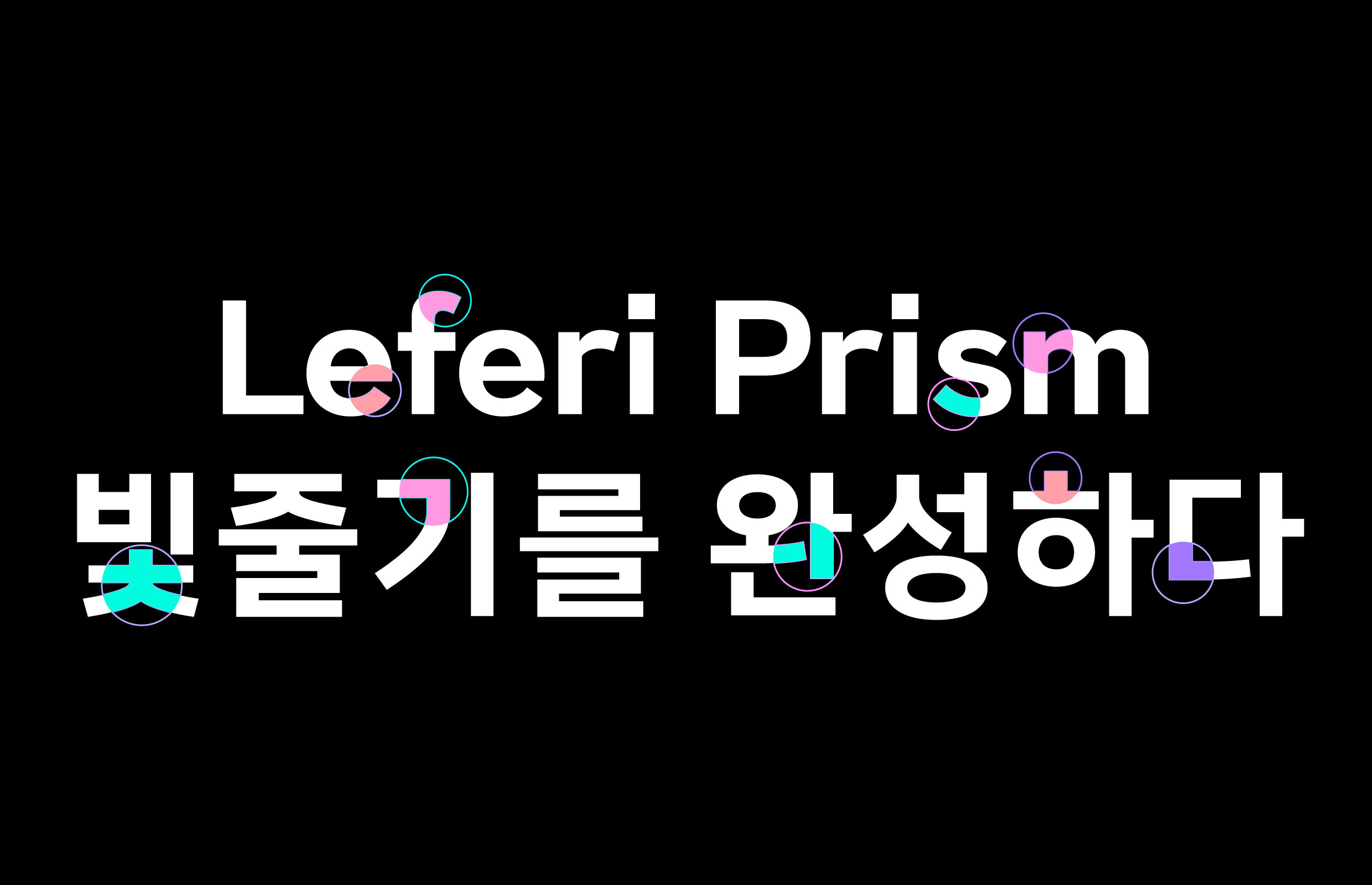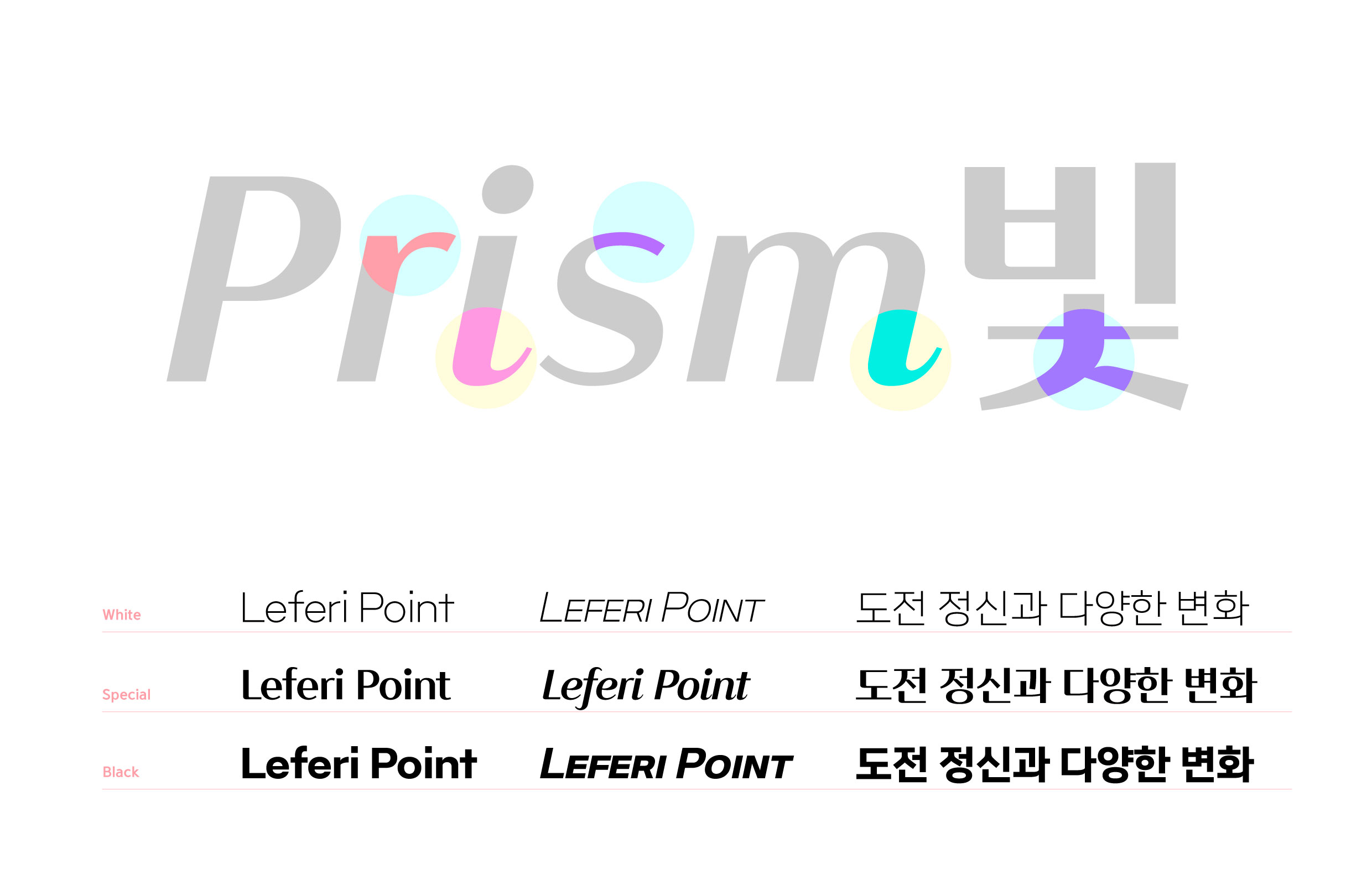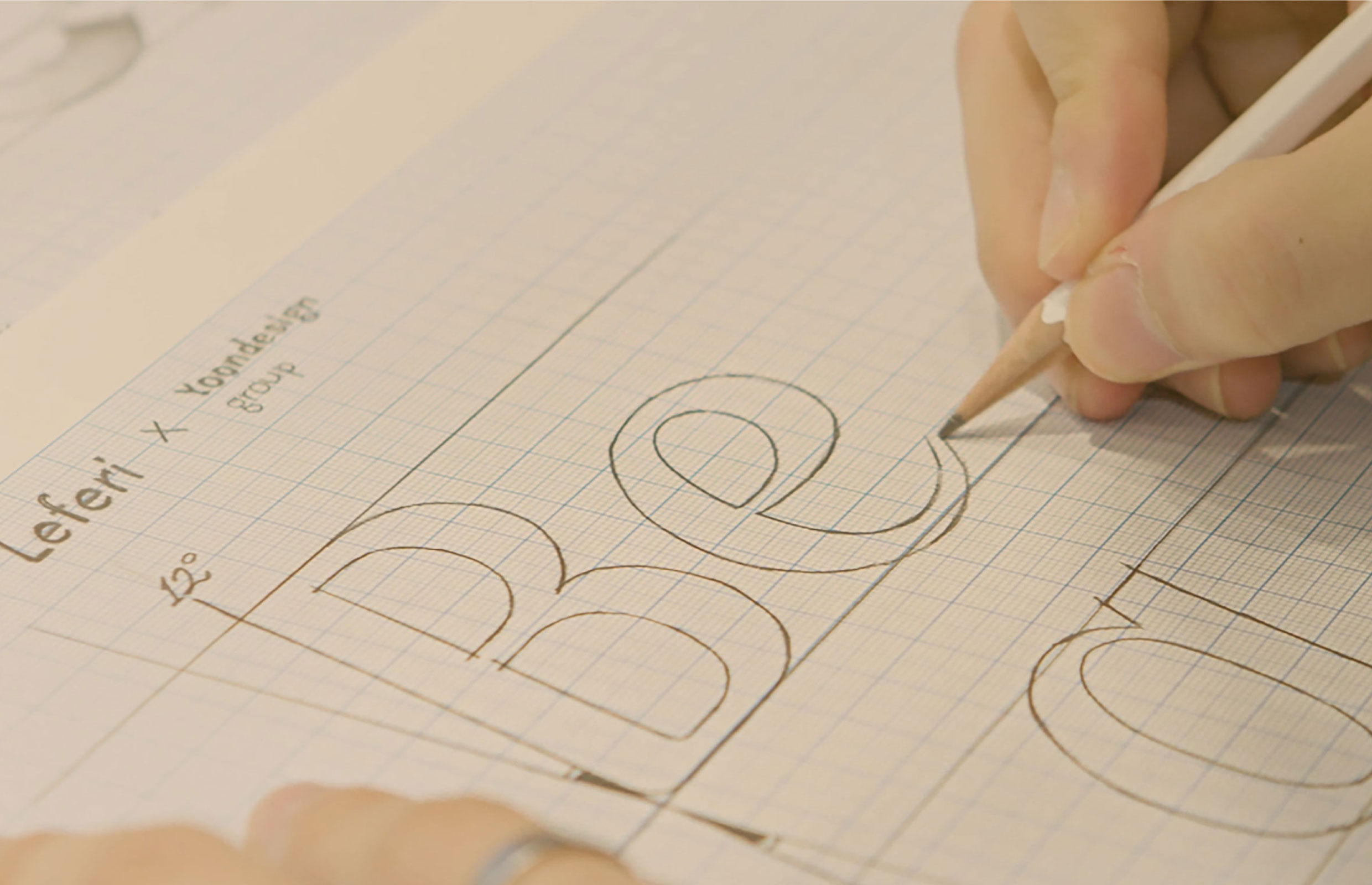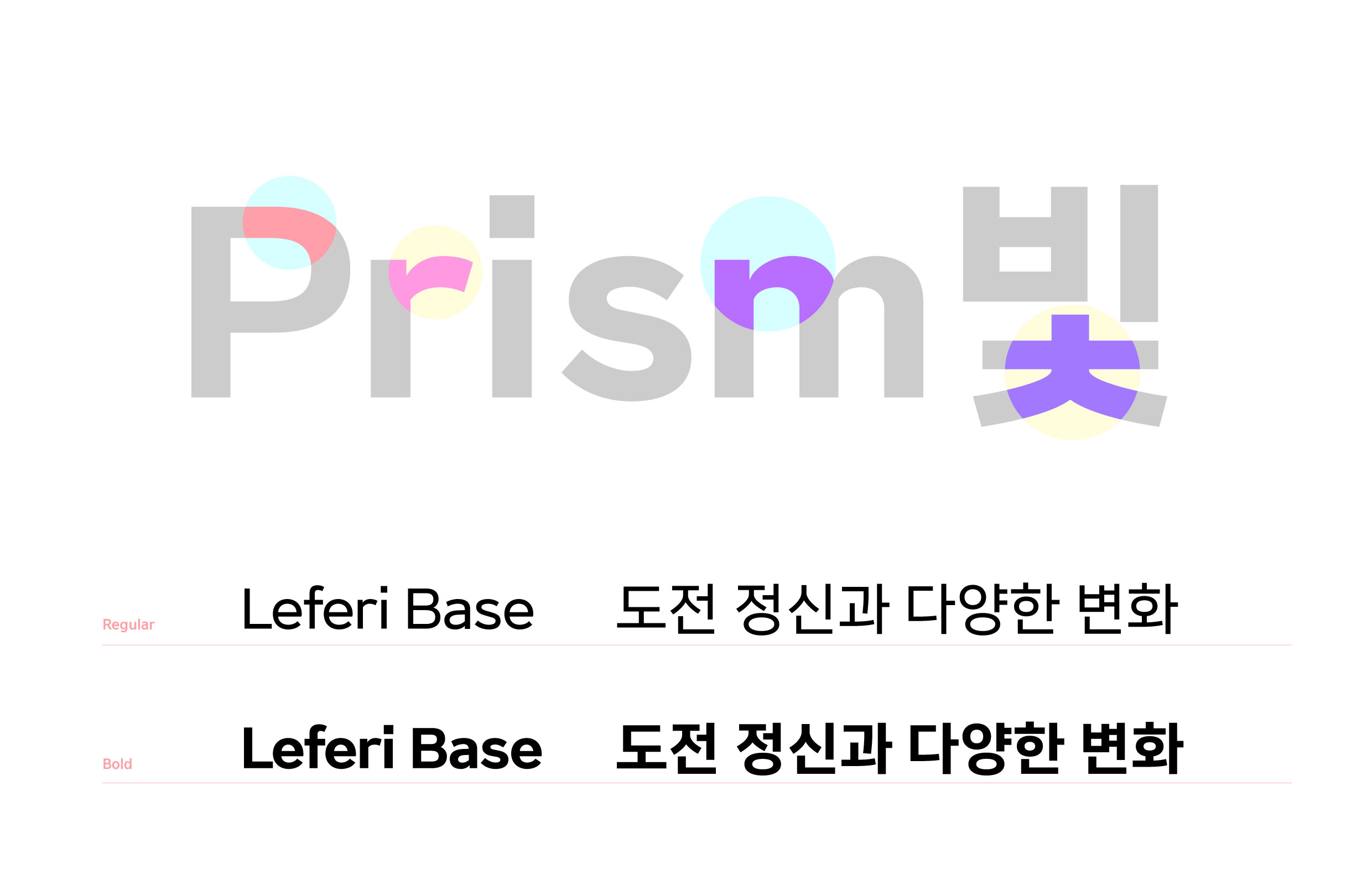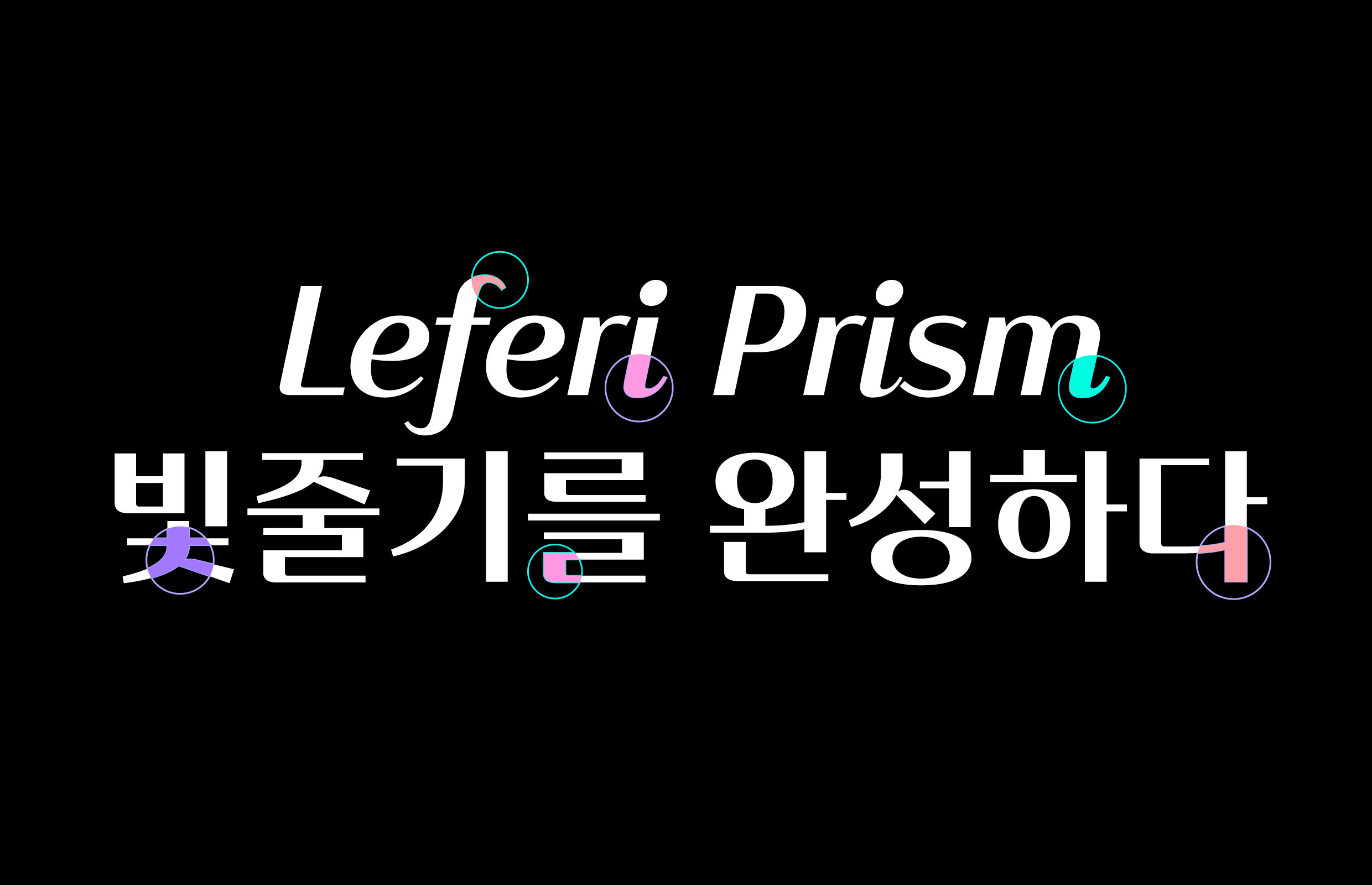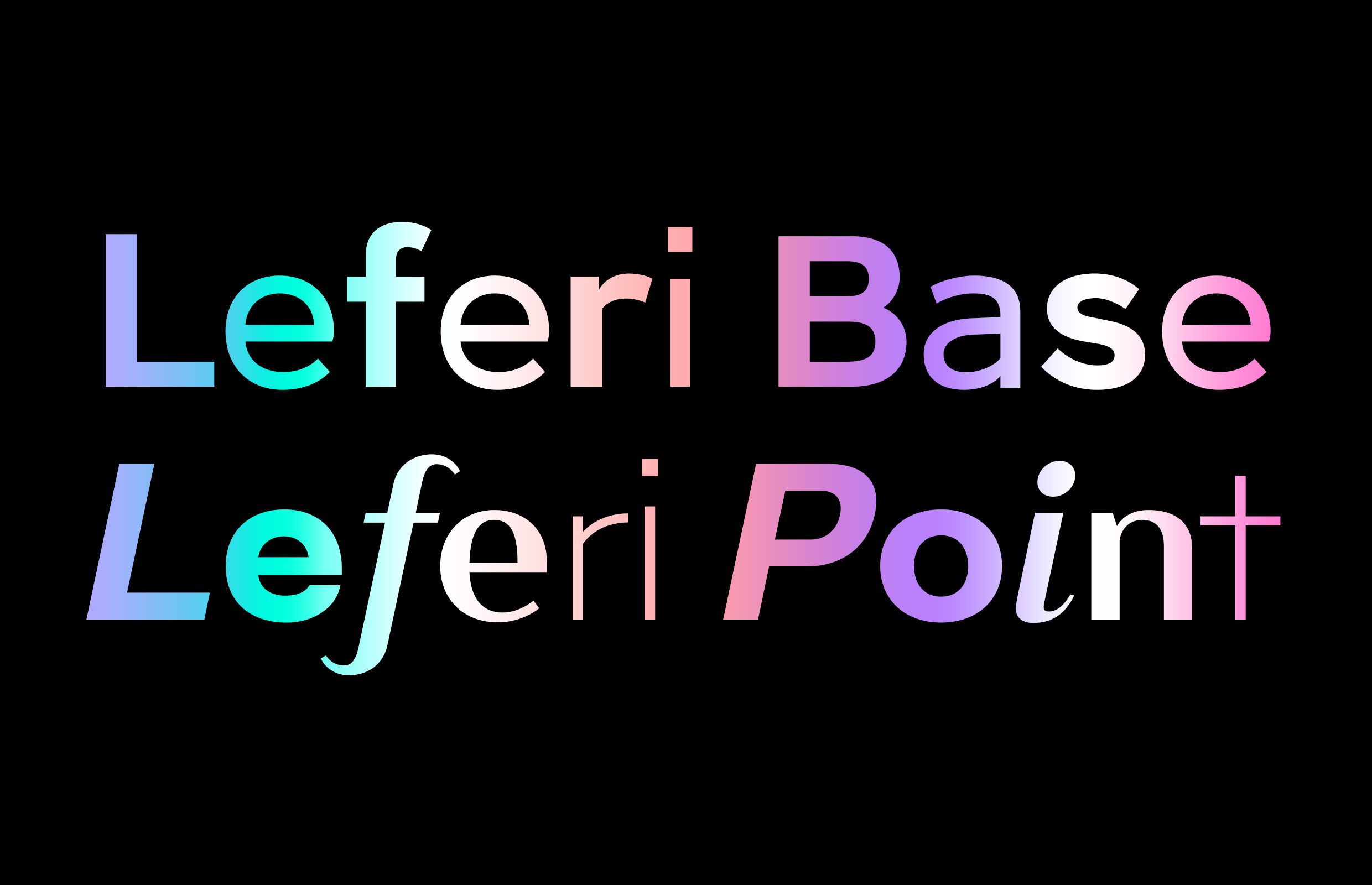
레페리 [레페리 전용서체]
도전 정신 충만한 모든 크레이터를 포괄한다는 의미로 ‘프리즘'이라는 디자인 콘셉트를 적용했다. 레페리 타입 패밀리 네임인 ‘베이스'와 ‘포인트'는 메이크업 용어에 영감을 받은 것이다. 포인트 타입은 아이덴티티 전달에 초점을 맞춰 극적인 굵기로, 베이스 타입은 커뮤니케이션을 위해 일반적인 굵기로 각각 구성했다.